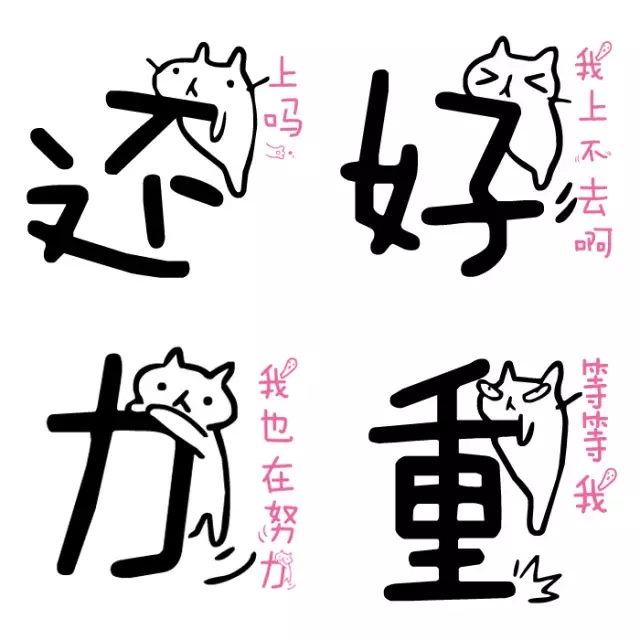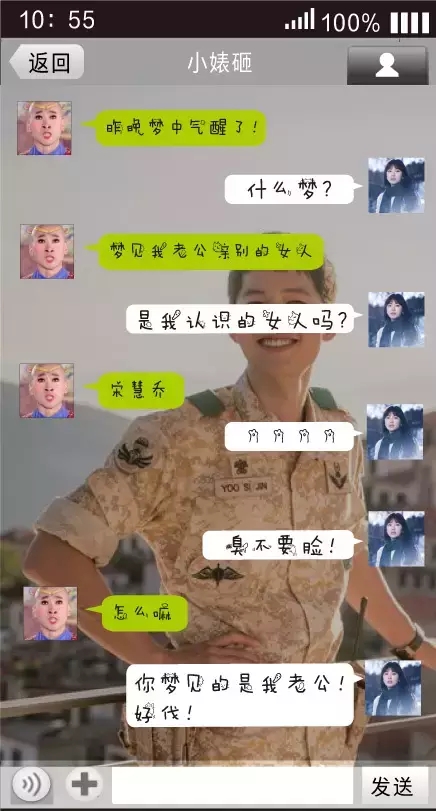
字体推荐:方正有猫在
前方高能预警!一大波“喵星人”正向你的屏幕走来,它们有着极具杀伤力的“蠢萌”武器,能让你的心连同名字一起瞬间萌化,不信,你看——
名字里“有猫在”的美妙,你们感受下
不仅有猫,还是不同表情的猫哦~
这些“喵星人”都属于同一个品种——
方正有猫在简体
它们酷酷的主人即将登场,请准备好尖叫声——
喵呜
知名漫画家,方正喵呜体设计师。已出版漫画绘本《有猫在》1-4册、《消费侠》、《羞怯的城市》、《丫头》。
用“方正有猫在”字体输出的部分文字及符号
不仅汉字配有萌萌的猫咪图案
设计师还专门设计了72个猫咪表情符号
有了“方正有猫在”,撩汉技能瞬间get√